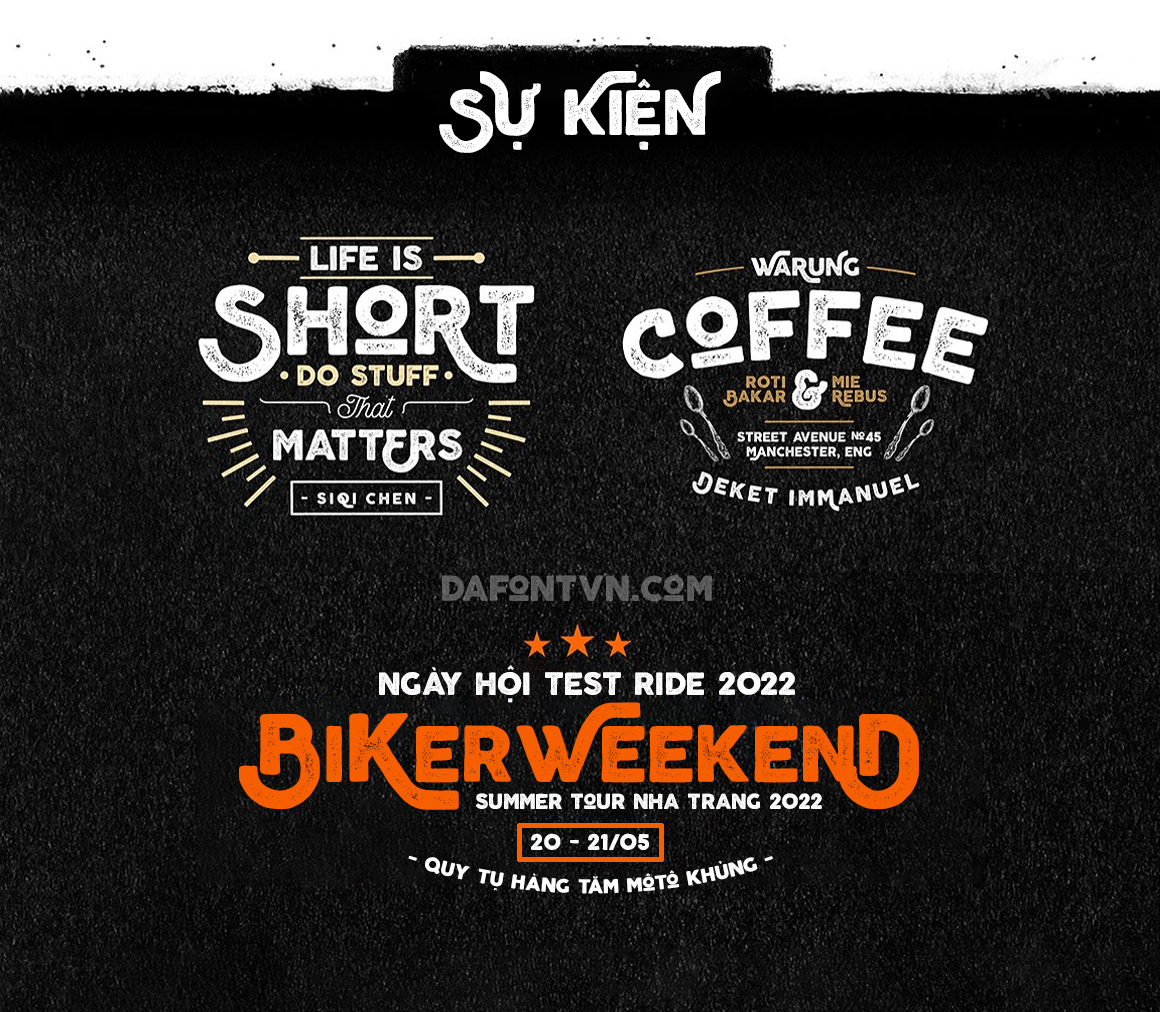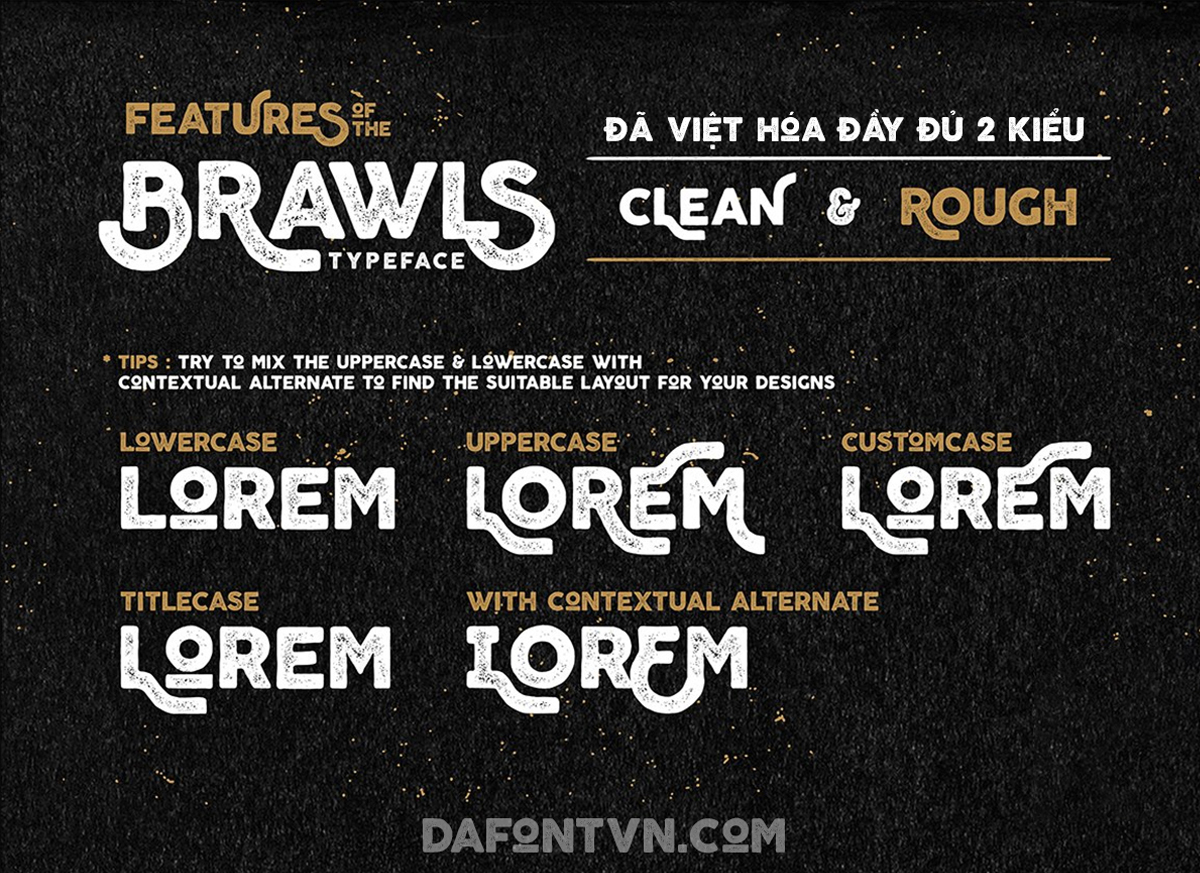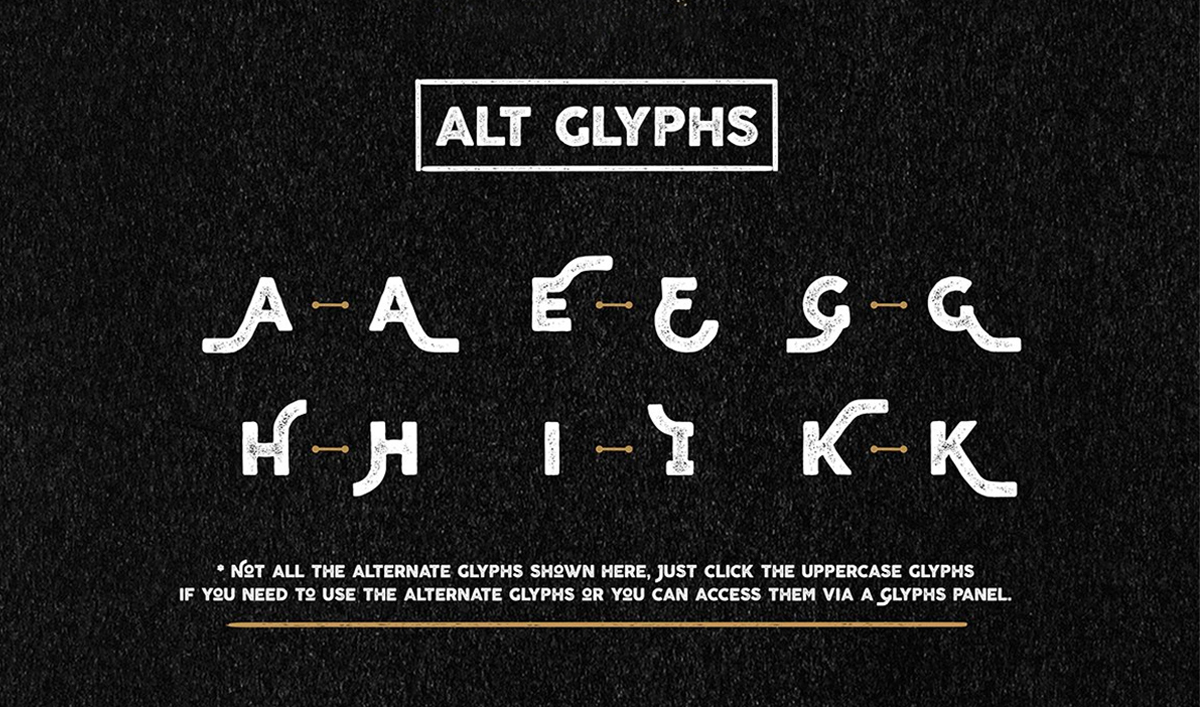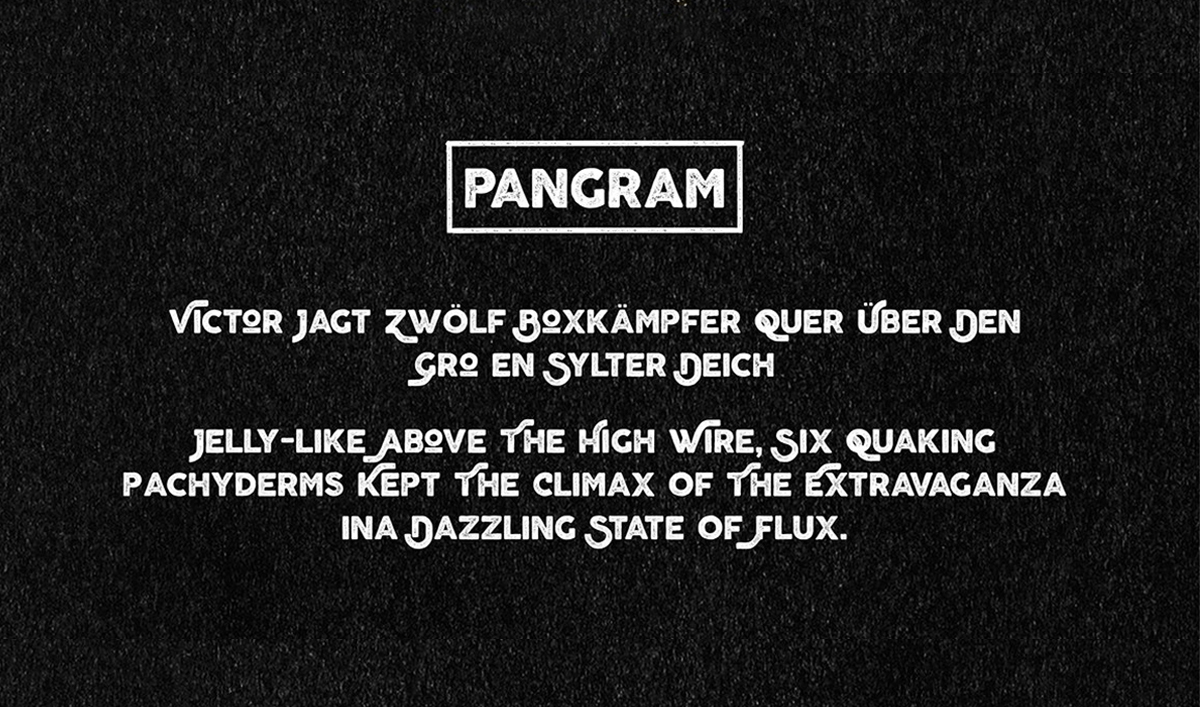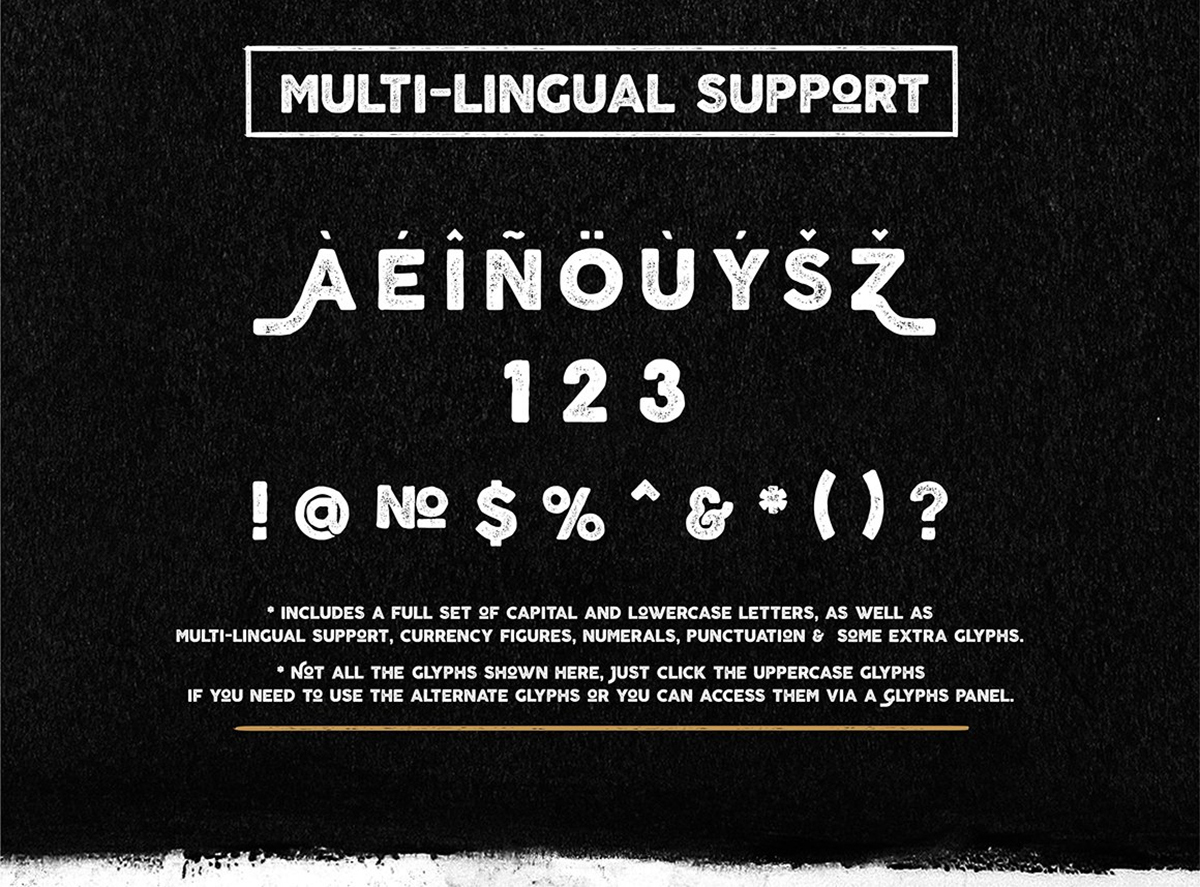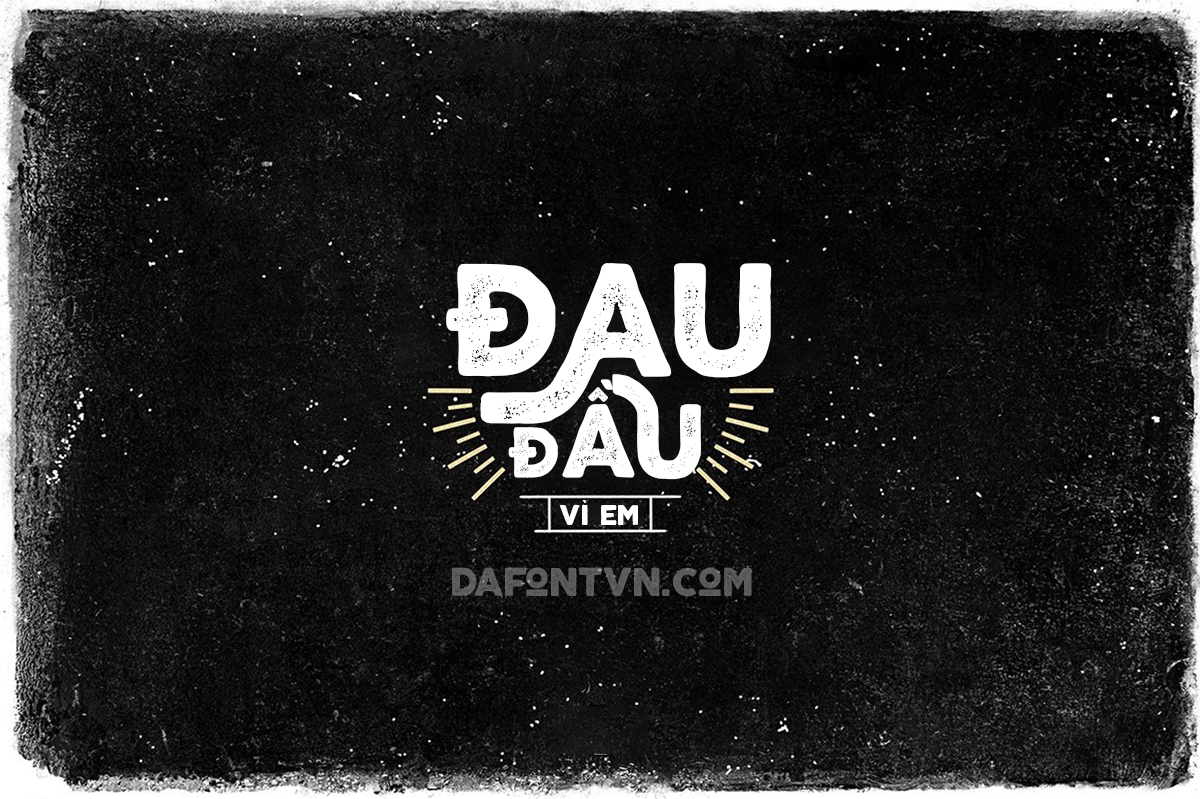
Font Brawls Typeface Việt Hóa (đầy đủ 2 kiểu)
Font Việt Hóa Brawls Typeface – là một phông chữ với bộ ký tự đơn giản, tối giản mong phong cách cổ điển và hiện đại. Đi kèm với 2 kiểu khác nhau cùng với đó là các chữ hoa và chữ thường, bạn có thể kết hợp với glyph thay thế.
Bao gồm 2 kiểu đã việt hóa đầy đủ, kerning, chỉnh sửa và tối ưu: